TOP 10 FONT CHỮ KHÔNG CHÂN ĐẸP NHẤT 2022
Hiện nay đã và đang tồn tại vô số font chữ khác nhau mà mỗi kiểu lại có những nét độc đáo riêng biệt. Thế nhưng phổ biến nhất lại là các font chữ không chân: vừa dễ đọc lại vừa đơn đơn giản.
Trong bài viết này IoTStartUp sẽ chia sẻ tới bạn đọc tất tần tật thông tin về font chữ không chân và top 10 font chữ San Serif đẹp nhất dưới đây.
Font chữ không chân đẹp, kiểu chữ không chân là gì?
Font chữ không chân đẹp là gì?
Font chữ không chân Sans-serif về cơ bản là phông chữ không có gạch nối nhỏ ở cuối mỗi ký tự; chẳng hạn như Times New Roman. Về mặt từ nguyên, từ “Sans” được xuất phát từ tiếng Hà Lan cổ; và nó có nghĩa là “gạch ngang” hoặc “dòng”, và “serif” có nghĩa là “không có” trong tiếng Pháp. Vậy bạn sẽ nhận được gì nếu bạn để 2 từ này lại với nhau? Hai từ này ghép lại nghĩa là font chữ không chân hay kiểu chữ không chân.
Phông chữ serif (có chân) về cơ bản là một font chữ với một vài đường cong; và dấu gạch nối ở đuôi và thân của mỗi ký tự chữ cái. Sans serifs (không có gạch chân) thì ngược lại, và nó có xu hướng sẽ được nhìn thấy nhiều hơn trong tương lai. Sans serif hay serif thì là font chữ dễ đọc? Câu trả lời là tùy vào từng trường hợp và khác nhau theo ngữ cảnh.
Đối với các văn bản dài, một số nhà nghiên cứu cho rằng phông chữ serif cải thiện khả năng đọc; trong khi những phông chữ khác không thấy nhiều sự khác biệt.
Cho đến gần đây, font chữ không chân được ưa thích hơn cho văn bản. Vì sự dễ nhìn, đơn giản cũng như dấu hiệu và biểu trưng của các ký tự. Tuy nhiên, phông chữ serif đã được hồi sinh để chống lại sự thống trị của xu hướng phông chữ sans-serif trong những năm trở lại đây.
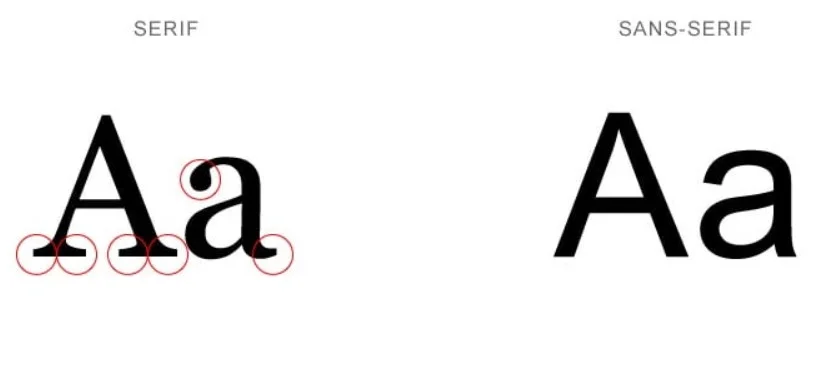
Nguyên tắc sử dụng font chữ này vô cùng đơn giản. Bạn có thể dùng để chia sẻ thông tin một cách rõ ràng, dễ đọc và trực tiếp. Font chữ này không dùng in đậm hay siêu đậm cho văn bản dài mà thiên về các nét ký tự mỏng hơn.
Sans Serif cực kỳ linh hoạt và hỗ trợ nhận dạng nhiều thương hiệu ưa thích sự đơn giản. Các ngành như công nghệ, thể thao, thời trang, ô tô,… là những ngành thường xuyên sử dụng font chữ không chân để quảng bá thương hiệu.
Một số ứng dụng của font không chân
Ngày nay, các font chữ San Serif được áp dụng khá nhiều trong đời sống ở nhiều lĩnh vực khác nhau như:
- Thiết kế giao diện người dùng (UI) trở nên dễ nhìn hơn đã trở thành sự lựa chọn của nhiều nhà thiết kế giao diện. Ngoài ra chúng còn giúp khách hàng không bị rối chữ hay mỏi mắt khi đọc.
- Nhận diện thương hiệu: Không có sự cầu kỳ, mềm mại như Serif, font chữ không chân lại đề cao sự đơn giản, tinh tế nhưng vẫn hiện đại. Chính vì thế nhiều thương hiệu lớn đang có nhu cầu xây dựng thương hiệu gần gũi, thân quen đã và đang chọn Sans Serif.
Font chữ này cực kỳ thích hợp cho thiết kế logo, nhận dạng thương hiệu, giúp người xem nhớ được tên tập đoàn, doanh nghiệp ngay từ cái nhìn đầu tiên.
Top font chữ không chân đẹp nhất 2022
Font không chân Helvetica Now
Theo số những font chữ không chân phổ biến trên thị trường hiện nay; thì Helvetica Now có thể được xem là font chữ có tầm ảnh hưởng lớn nhất từ trước đến nay. Microsoft, Jeep….đều đang rất ưa chuộng sử dụng font chữ Hellbeta; để thiết kế logo và nhấn mạnh thương hiệu của họ trong nhiều năm.
Font chữ này trông rất mạnh mẽ và dễ nhìn. Với việc phát hành Helvetica Now vào năm 2019; Monotype đang củng cố di sản của một trong những serifs sans phổ biến và đẹp nhất từng được tạo ra.
Proxima Nova
Proxima Nova là một trong những font chữ không chân cổ điển khác trong thế giới sans-serif. Nó trông tuyệt vời và phổ biến với cả nhà sản xuất logomaker; và nhà thiết kế UX. Nếu gần đây bạn đã kiểm tra tài khoản Spotify của mình; bạn sẽ thấy rằng đây là phông chữ hệ thống đang được sử dụng cho các tên bài hát; và tên những nghệ sĩ của họ.
Phông Sans Serif không chân Futura
Có từ năm 1927, Futura là một kiểu chữ không chân hình học tuyệt đẹp; dựa trên các hình dạng hình học hiện đại, đặc biệt là hình tròn. Được thiết kế bởi Paul Renner, Futura là một gia đình kiểu chữ thực sự thanh lịch; mạnh mẽ và hiện đại đã chuyển mình sang thời đại kỹ thuật số.
Font Sans Serif Coco
Sinh ra để các nhà thiết kế áp dụng vào logo trong lĩnh vực thời trang, Coco là font chữ không chân có sự thanh lịch và sang trọng. Coco là một trong những font chữ không chân miễn phí, tích hợp 8 kiểu đậm nhạt khác nhau nhưng vẫn mang nét cổ điển hòa trong sự hiện đại, đơn giản của nó.
Peace Sans
Peace Sans là font chữ thường được dùng cho các tiêu đề để nhấn mạnh. Nó dễ đọc, nổi bật, khá bắt mắt với người xem. Nhưng tính đến thời điểm hiện tại, font chữ không chân này chỉ cos1 kiểu font nhất định. Vì thế bạn nên kết hợp với màu sắc, hình ảnh để font chữ được nổi bật hơn.
Font chữ không chân Mosk
Được sáng tạo và thiết kế bởi Lulian Maftei, font chữ không chân Mosk mang trong mình nét thanh lịch nhưng lại rất táo bạo, đặc biệt. Mosk cung cấp độ đậm nhạt của chữ đa dạng trên thang đo từ 100 đến 900. Đây thực sự là một Sans Serif gây ấn tượng mạnh với người dùng cũng như người xem.
Millimetre
Lấy nguồn cảm hứng dồi dào từ toán học. Millimetre là font chữ miễn phí khá được yêu thích hiện nay. Font chữ Sans Serif này đã và đang hỗ trợ tới 17 ngôn ngữ khác nhau nhưng chưa có bản tiếng Việt do Jérémy Landes sáng tạo ra. Không chỉ có vậy, font chữ này còn có 2 font khác là Millimetre Regular và Millimetre Bold.
Manrope
Manrope mang nét nhẹ nhàng, đơn giản nhưng cũng không kém phần tinh tế. Ngày nay, font chữ này có 7 kiểu chữ từ in đậm, in nghiêng,… làm gia tăng sự lựa chọn của bạn nhưng vẫn giữ được nét dễ đọc cho người nhìn. Manrope thường được dùng khi thiết kế website hay những tập dữ liệu thông tin dài.
Bebas Kaih
Bebas Kai là một font chữ không chân mang phong cách của Ấn Độ. Font chữ này hợp thời trang, đơn giản, dễ nhìn, dễ đọc nhưng cũng khá lạ mắt và tạo được điểm nhấn. Bạn có thể dễ dàng sử dụng chúng cho mục đích cá nhân hay xây dựng một thương hiệu hay dùng để phát triển dự án đều được.
Font không chân Work Sans
Font chữ cuối cùng nằm trong danh sách chính là Work Sans. Font chữ không chân này đậm tính hiện đại, luôn đứng đầu xu hướng. Ngoài ra, Work Sans còn được tích hợp thêm 17 kiểu chữ khác nhau, tạo nên sự đa dạng và phong phú.
Nhiều người thường sử dụng Work Sans cho các văn bản in ấn, là font chữ ưa thích ở mảng kỹ thuật số.
Trên đây là những thông tin về các font chữ không chân đẹp hiện đại và phổ biến. Hy vọng bài viết trên sẽ giúp bạn lựa được kha khá font chữ không chân hiện đại cho mình